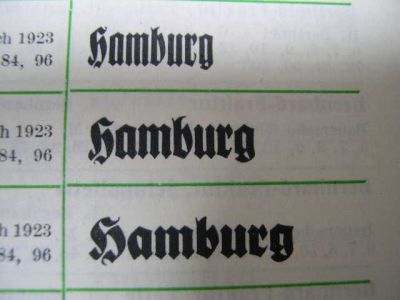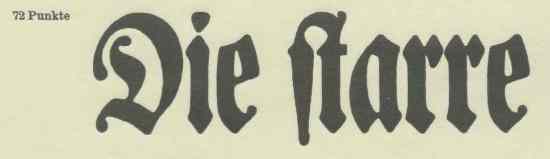
Frakturschrift --- ähnlich "Schmale Anzeigenschrift&quo
im Jahre 1975 wurde unter der Marke "Parker Spiele" in Deutschland ein Spiel namens "Duell --- Mit den Waffen des Geistes" auf den Markt gebracht. Für den Satz des Spielenamens auf der Verpackung wurde eine gewisse Frakturschrift benutzt (s.u.). Weitere Bilder dazu findet Ihr auch unter dem folgenden URI:
Wer kann die benutzte Schrift namentlich identifizieren?
Eine Ähnlichkeit mit "Schmale Anzeigenschrift" ist nicht zu übersehen. Handelt es sich möglicherweise um die "Breite Anzeigenschrift"?
Aaah – ich kenne sie, ich kenne sie – bloß, wie heißt sie noch? Also, Whatthefont bringt leider keinen echten Treffer, aber es gibt hier jemand, dessen Spezialthema dies ist. :wink:
Die Deutsche Anzeigenschrift ist es mE nicht.
Zum Vergleich
oben Deutsche Anzeigenschrift breit
unten Deutsche Anzeigenschrift schmal
Ich vermute, daß es sich bei dem Beispiel um eine gezeichnete oder stark bearbeitete Schrift handelt.
Ich denke das ist die schmalfette Bernhard-Fraktur - wenn ich meinem alten Schriftmusterbuch trauen darf - mit 72 Punkt.
Ein gewisser Dipl.-Ing. Gerhard Helzel bietet im Netz an die folgenden Schnitte von "Bernhard Fraktur": mager, 24 Punkt; extrafett, 20 Punkt. Den Angaben nach handelt es sich um Digitalisierungen einer gleichnamigen Schrift bzw. von Schnitten davon eines gewissen Prof. Lucian Bernhard (tatsächlicher Name Emil Kahn) von 1922. Nicht im Angebot ist der Schnitt schmalfett.
Die Schriftproben der angebotenen Schrift bzw. Schnitte unterscheiden sich jedoch recht deutlich von dem Schriftzug des Spiels "Duell" als auch von der Schriftart in der Graphik von Zainer, insb. beim großen D.
Kann der Schnitt (halbfett) bzw. die Größe (72 Punkt) tatsächlich eine --- auch stilistisch --- derart verschiedene Darstellung des großen D bedingen?
Anders gefragt: Ist die in der Graphik von Zainer benutzte Schrift tatsächlich die Bernhard Fraktur? Wer kann dies bestätigen? Bitte melden!
Bernhard-Fraktur fett
Schriftgießerei: Flinsch
Erstguß 1912
Entwurf Lucian Bernhard
Eine Digitalisierung der Bernhard-Fraktur durch Herrn Helzel wird ausdrücklich vom Klingspor-Museum genannt - was seine Arbeit wohl anerkennt.
Die extrafette Version der Bernhard-Fraktur wurde von der Bauerschen Gießerei erstellt.
im Jahre 1975 wurde unter der Marke "Parker Spiele" in Deutschland ein Spiel namens "Duell --- Mit den Waffen des Geistes" auf den Markt gebracht. Für den Satz des Spielenamens auf der Verpackung wurde eine gewisse Frakturschrift benutzt (s.u.). Weitere Bilder dazu findet Ihr auch unter dem folgenden URI:
Wer kann die benutzte Schrift namentlich identifizieren?
Eine Ähnlichkeit mit "Schmale Anzeigenschrift" ist nicht zu übersehen. Handelt es sich möglicherweise um die "Breite Anzeigenschrift"?
Dieses Muster zeigt - von oben nach unten:
Deutsche Anzeigenschrift, Enge
Deutsche Anzeigenschrift, Schmale
Deutsche Anzeigenschrift, Breite
Ich kann keine Ähnlichkeit zu Deinem Muster "Duell" erkennen.
Auch die Bernhard-Fraktur ist es nicht.
Ist dieses Buch bekannt?
Handbuch der Schriften
Albrecht Seemann, Leipzig
Genannt "Der Seemann", 1926
In diesem Buch befinden sich so gut wie alle bis 1926 herausgegebene Bleisatz-Schriften. Von allen Schriften gibt es ein Schriftmuster am Beisp8iel des Wortes "Hamburg". Warum Hamburg? Ich weiß es nicht, aber ich habe mir schon manchmal verzweifelt ein anderes Wort gewünscht, egal.
Im Seemann ist Deine "Duell"-Schrift nicht enthalten.
Ich bin von den eigenartig gerundeten Serifen der "ll" ausgegangen. Habe daraus geschlossen, daß das "b" ähnlich entworfen ist. Eine solche Fraktur-Schrift finde ich dort nicht.
Mein Schluß:
Diese Schrift ist modifiziert und keine Original-Schrift.
um einem möglichen Mißverständnis vorzubeugen – meine Abbildung stammt von einer Bleitype.
Natürlich ist die schmalfette Variante der Bernhard-Fraktur aus eben derselben entwickelt worden; es ist aber eine völlig eigenständige Type. Von dieser Type gibt es für verschiedene Kegelhöhen unterschiedliche Schriftschnitte. Das von dir gezeigte Beispiel kann eben nur von einem besonderen Schnitt für große Kegelhöhen (ab 20 Punkt) stammen.
Du kannst dir das in etwa so vorstellen wie die Optical Pro Schriftfamilien von Adobe, die zwar zusammengehören, für verschieden große Zeilenhöhen aber auch leicht unterschiedliche Schnitte haben.
Ich bezweifle, daß die schmalfette Bernhard-Fraktur je digitalisiert wurde. Die digitalisierte (normale) Bernhard-Fraktur wird aber nie genau das Schriftbild zeigen wie in deinem Beispiel. Daher wirst du wohl eine andere Schrift suchen müssen.
Um doch noch zu einer kostengünstigen privaten Website zu kommen, würde ich eine ähnliuche Frakturschrift als Vorlage nehmen und dann nachbearbeiten, schließlich geht es nur um fünf Buchstaben und nicht um einen Roman. Die erreichbare Ähnlichkeit zum Originalschriftzug ist sicher so groß, dass kein Besucher der Website den Unterschied sehen wird -- okay für achtzig Prozent der Leser könntest du auch Schwabacher nehmen und sie würden den Unterschied nicht sehen.